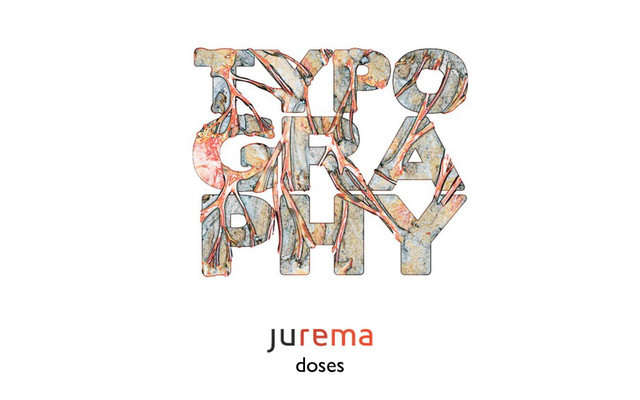
Tipografia
primeiras escritas...
ROMANA Gótica Corsiva
esculpir em madeira | carimbo | xilogravura
Johannes Gutenberg 1439 PRENSA
Johannes Gutenberg 1439 IMPRENSA
tipos metais organizar linhas de tipo caixa alta/baixa
Nomenclaturas | fontes digitais | css serifa - kerning -
baseline
máquina inspetor bugiganga cunhar linha tipográfica espécie de teclado
Revolução | Editorias
gravuras tipográficas
Tipógrafos | Famílias tipográficas
Garamond 1540
Bodoni & 1798
1800
Cooper Black 1921
1927
1967
Milton Glaser New York State marketing campaign 1977
Comic Sans 1994 Microsoft
tipografia que fala
ibm bitmap typewriter
primeira tipografia digital
Open Type | 1997
criação de tipografia font lab
Escolho uma tipografia!? Crio uma tipografia? Roubo uma tipografia?
legibilidade identidade aplicação Escolha uma fonte com o estilo adequado
Deixe o corpo no mínimo 12px - 16px De que modo a tipografia será aplicada
Legibilidade Kerning Entrelinhas/Densidade Extensão da linha Tamanho da fonte
@font-face {} | css rule | web safe fonts
Keep in mind Qual a finalidade do projeto? Quem vai
ler e de onde? Dúvida? aumenta a tipo